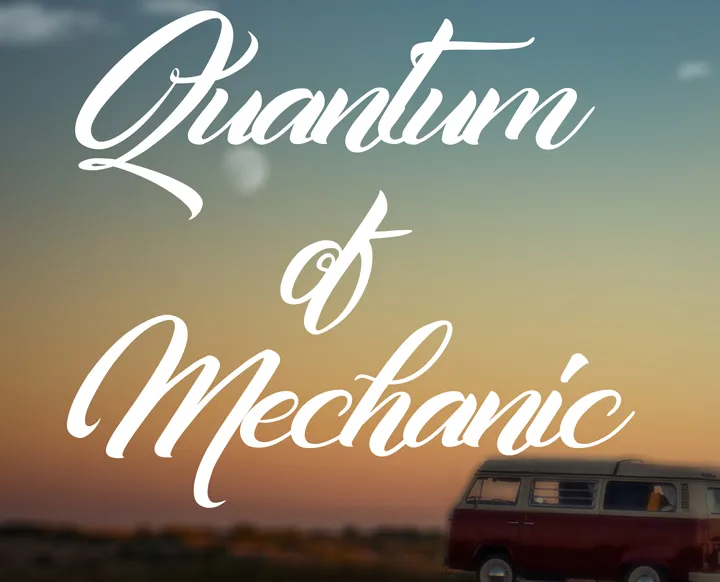
Aqui está uma descrição envolvente e natural para a página de download da fonte ‘Quantum of Mechanic’, categorizada como Calligraphy Fonts: Se você busca fontes artísticas de alta qualidade, seu objetivo pode estar encontrado nesta bela letra escritura. Selecione o Quantum of Mechanic Font para adicionar um toque especial ao seu design pessoal ou projetos independentes. Este é um artigo que Cat Butcher criou com arte e talento, disponível gratuitamente para uso pessoal. Para qualquer aplicação comercial, contate Cat Butcher antes para obter permissão. Ele entende a importância de respeitar seus trabalhos e a necessidade de proteger seu trabalho original. Se você se interessar em trabalhar com ele ou tiver alguma dúvida sobre direitos autorais, pode entrar em contato através do email . Afinal, o Quantum of Mechanic Font traz um toque especial à sua página de design e certamente fará uma grande diferença ao tornar seus projetos mais atraentes. Descubra o poder da arte e comece a explorar agora.